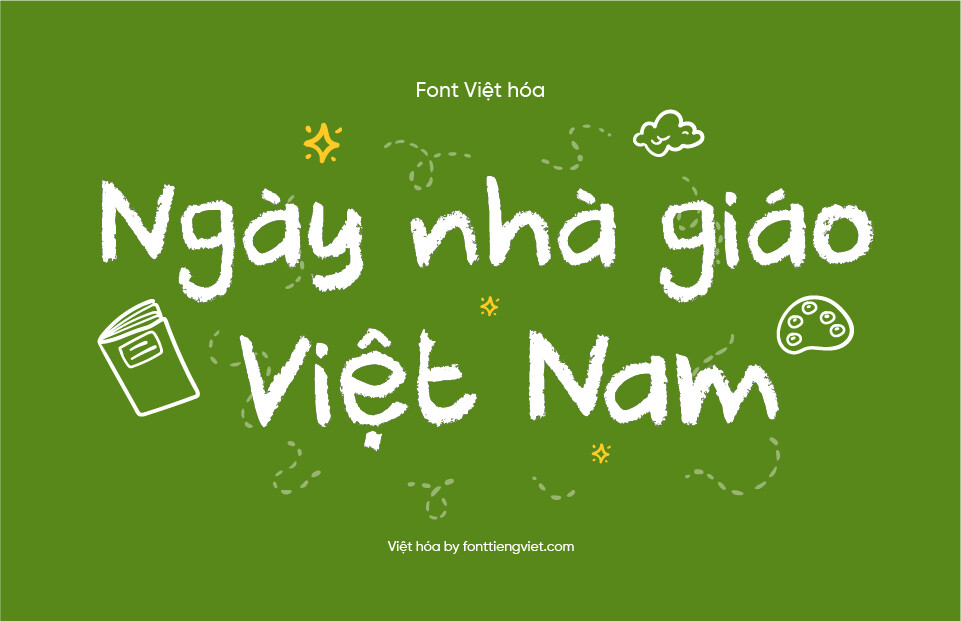
Font Việt hóa 1FTV VIP DK Cool Crayon – Phấn
Font Việt hóa 1FTV VIP DK Cool Crayon – Phấn: Lựa chọn tuyệt vời cho giáo dục
Giới thiệu về Font Việt hóa 1FTV VIP DK Cool Crayon – Phấn
Trong thiết kế đồ họa dành cho trường học, việc tìm kiếm một bộ Font Miễn Phí có phong cách bảng đen phấn trắng là điều vô cùng cần thiết. Font Việt hóa 1FTV VIP DK Cool Crayon – Phấn chính là giải pháp hoàn hảo mang lại cảm giác hoài niệm và gần gũi. Bộ font này tái hiện chân thực những nét vẽ bằng phấn trên bảng, tạo nên sự sinh động cho các bài giảng hoặc các ấn phẩm truyền thông học đường.
Đặc điểm nổi bật của font chữ phấn viết
Bộ font này nổi bật với các nét vẽ thô ráp, mô phỏng lại độ nhám của phấn khi tiếp xúc với mặt bảng gỗ. Sự không hoàn hảo trong từng nét chữ chính là điểm nhấn giúp thiết kế trở nên tự nhiên hơn. Đặc biệt, phiên bản này đã được tối ưu hóa đầy đủ dấu tiếng Việt, giúp các thầy cô và học sinh dễ dàng sử dụng trong việc soạn thảo giáo án hoặc làm slide thuyết trình mà không lo lỗi hiển thị.
Cách ứng dụng Font Việt hóa 1FTV VIP DK Cool Crayon – Phấn hiệu quả
Bạn có thể sử dụng bộ chữ này cho nhiều mục đích khác nhau như thiết kế poster sự kiện trường học, trang trí menu quán cà phê phong cách vintage, hoặc làm thiệp chúc mừng thầy cô. Để đạt hiệu quả thị giác tốt nhất, hãy kết hợp font chữ này với phông nền màu xanh đậm hoặc đen bóng để làm nổi bật hiệu ứng phấn trắng.
Lưu ý khi sử dụng trong thiết kế đồ họa
Mặc dù mang tính nghệ thuật cao, người dùng nên sử dụng font ở kích thước vừa và lớn để đảm bảo khả năng đọc. Tránh dùng cho các đoạn văn bản quá dài vì cấu trúc nét nhám có thể gây mỏi mắt nếu trình bày ở định dạng nhỏ.
Kết luận về bộ font độc đáo